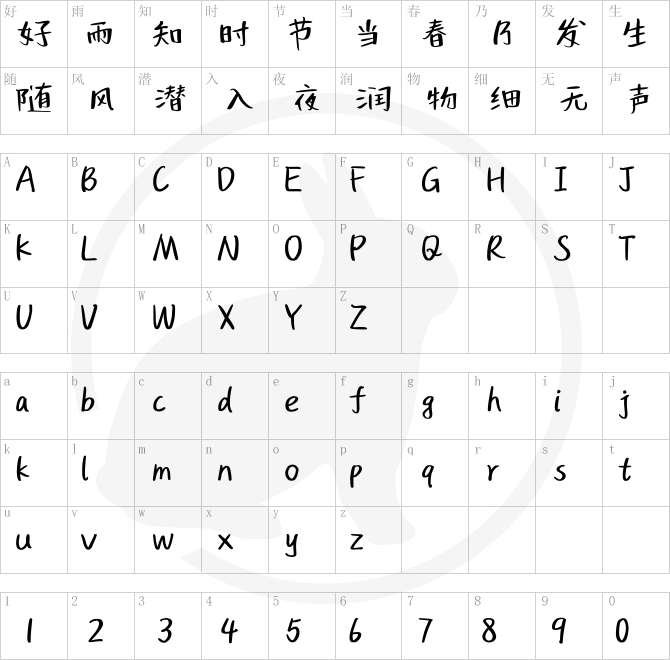
也字工厂企鹅体
也字工厂企鹅体,这款字体结构工整、笔画清晰,兼顾美观与易读性,适用于标题、正文、海报、包装、LOGO 等多种场景。字形优雅稳定,风格百搭耐看,适配日常排版与创意设计,让文字呈现更舒适、更具质感。也字工厂企鹅体一笔一画,皆是细节,以均衡的比例、流畅的线条打造舒适视觉体验,字形端正大气,风格简约现代。无论是商业设计、品牌宣传还是日常排版,都能轻松驾驭,让文字更有格调与力量。也字工厂企鹅体字体下载。